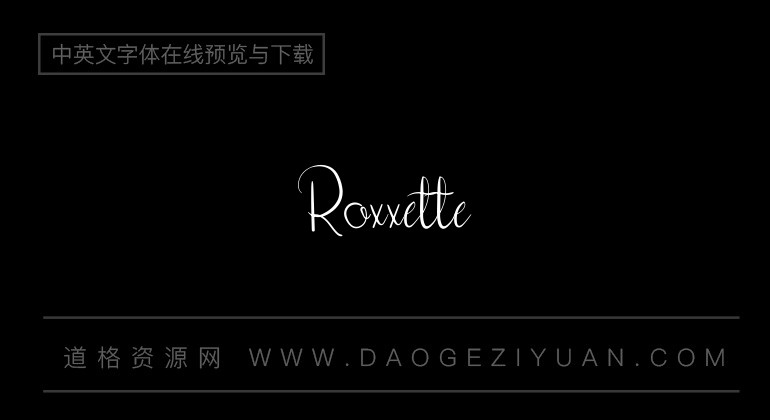
Roxxette是一款现代化的字体,具有流畅、简洁的设计风格。Roxxette字体家族由四种不同的字重组成,可以适用于各种设计和排版需求。 Roxxette字体的特点是其清晰度和易读性。它的字母设计简洁明了,每个字母都有清晰的边缘和线条。Roxxette字体也具有良好的比例和间距,使得它在各种不同的设计应用中都能表现出色。 Roxxette字体家族的四种字重分别为:Regular、Medium、Semi-Bold、Bold。这些字重可以满足不同设计需求,无论是标题、正文还是标识性文字,Roxxette都能提供出色的可读性和设计感。 总体来说,Roxxette是一款优秀的现代化字体,适用于各种设计和排版需求。内容介绍
Roxxette是一款非常不错的手写艺术字体,具有很好的视觉感,适合于文化类的宣传设计、商业类品牌的广告和产品包装设计以及个性化文字排版等较多场景。